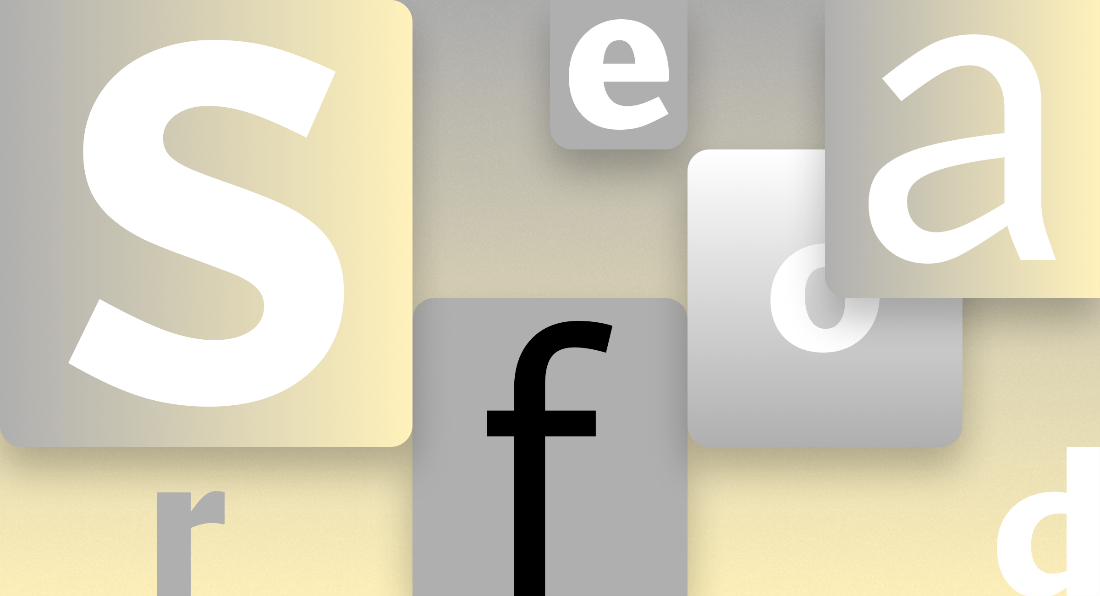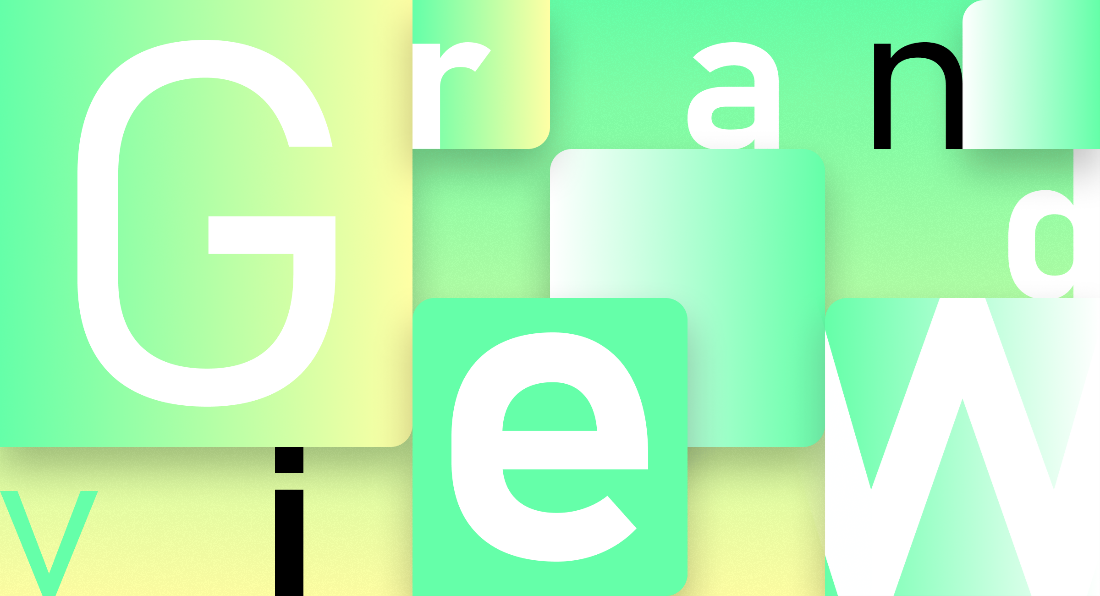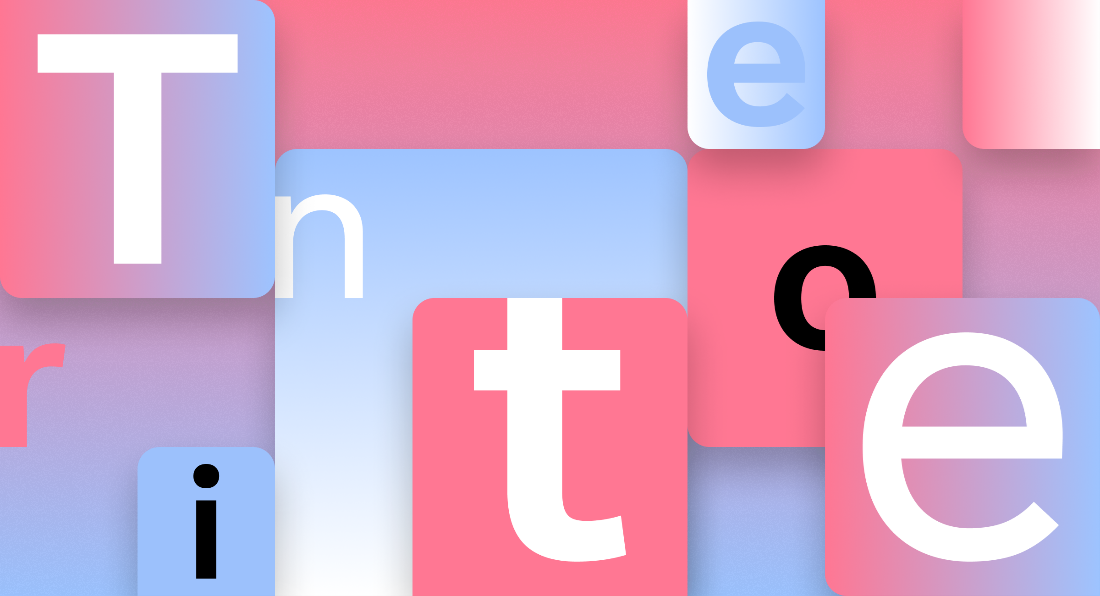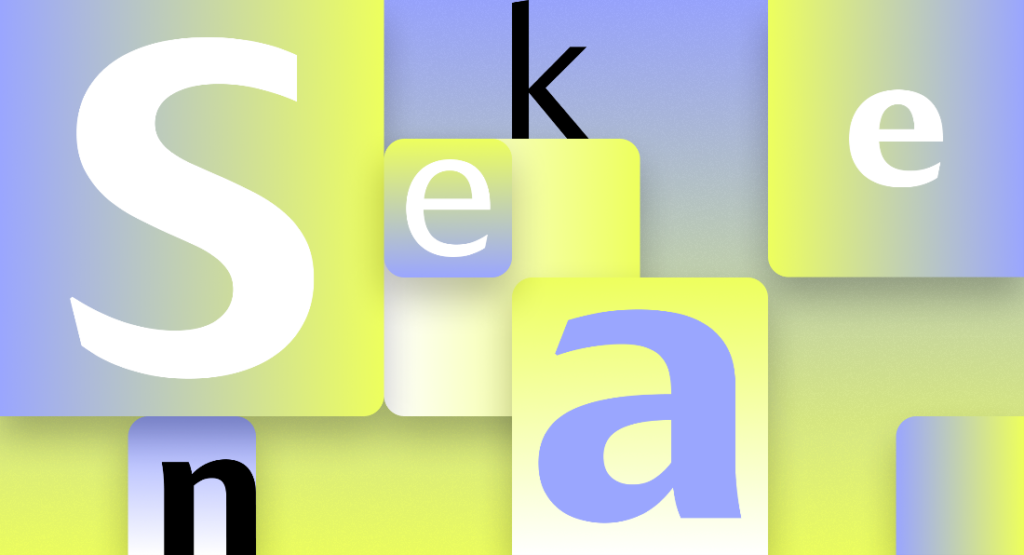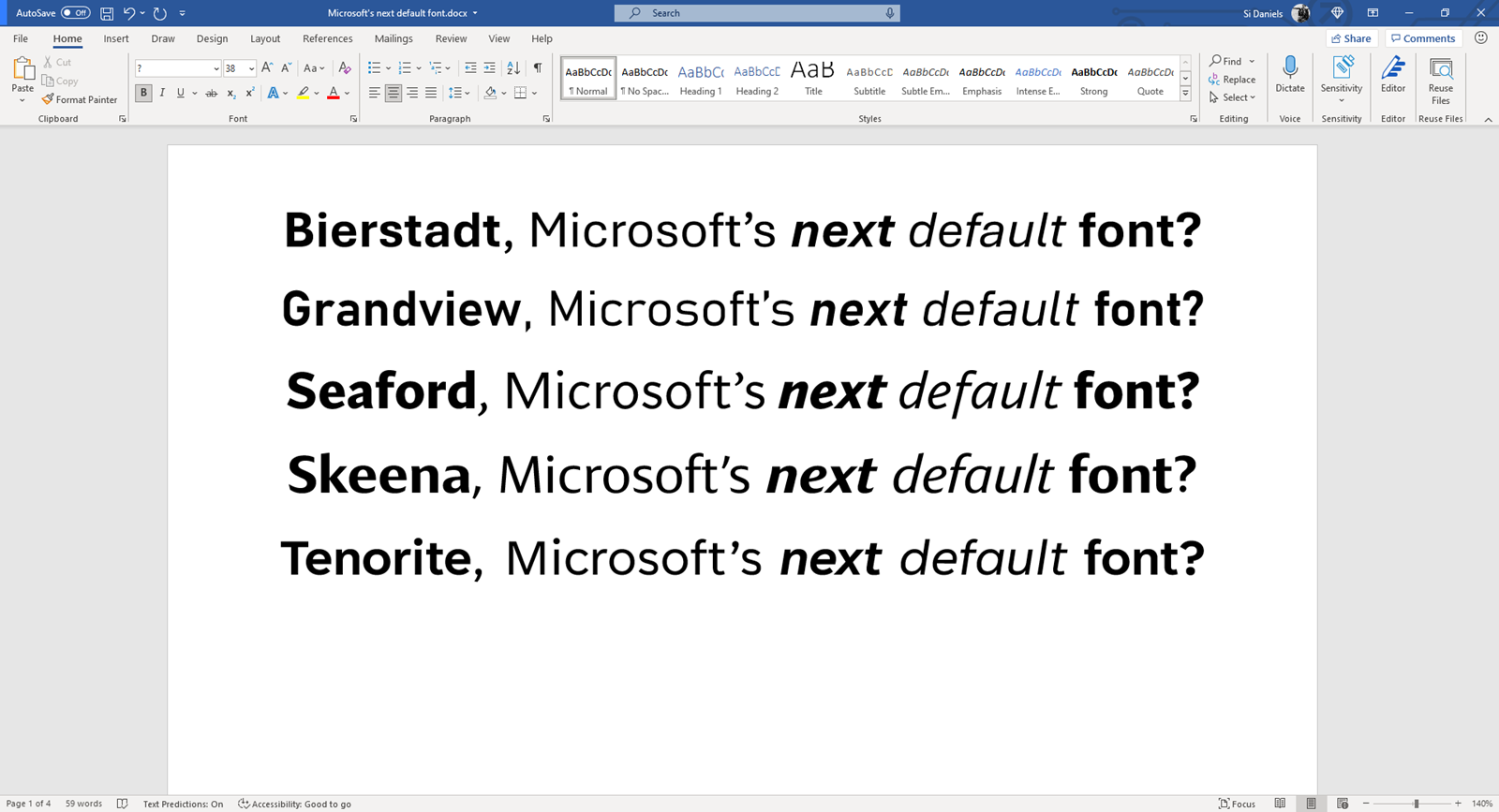
Microsoft mijenja zadani font Officea i traži povratne informacije korisnika
Calibri je korišten kao zadani font u Microsoft Officeu skoro 15 godina, pa Microsoft smatra da je promjena poželjna
Microsoft je objavio obavijest o zamjeni zadanog fonta unutar svoga programskog paketa Officea. Naime, promjena bi trebala stupiti na snagu već sljedeće godine, a tvrtka traži pomoć korisnika u vezi odabira novog zadanog fonta.
Korisnici će moći poslati povratne informacije u vezi pet novopredstavljenih sans serif fontova iz Microsoftove objave – Meet Tenorite, Bierstadt, Skeena, Seaford i Grandview. Navedeni fontovi sadrže, prema objavi tvrtke, razne stilove, uključujući humanistički, geometrijski, švicarski i industrijski.
Tenorite
Prvi od pet fontova, Tenorite, napravili su Erin McLaughlin i Wei Haung te izgleda najtradicionalnije. Iz Microsofta navode da Tenorite nalikuje Times New Romanu, ali da je više „topliji i srdačniji“. Font ima elemente kao što su velike točke, akcenti i interpunkcije koje ga čine ugodnijim za čitanje na zaslonu, a oštri mu oblici i široka slova daju na otvorenosti.
Bierstadt
Steve Mattison, inspiriran, švicarskom tipografijom iz sredine 20. stoljeća, napravio je drugi na listi font, Bierstadt. Naime, ovaj font nudi svestrani tip slova koja izražavaju jednostavnost i razumljivost u vrlo čitljivom obliku te je također vrlo jasno izražen završecima poteza koji ističu red, ali i suzdržanost. Bierstadt je nazvan po stjenovitoj planini u Koloradu koja je Mattisona podsjećala na švicarske Alpe.
Skeena
Treći je font Skeena, napravljen od strane Johna Hudsona i Paula Hanslowa, a inspiriran je raznim razdobljima dizajna fonta. Microsoft navodi da su potezi ovog fonta modularni s primjetnim kontrastom između debelih i tankih linija te da je idealan za tekst u dugim dokumentima, ali i kraćim odlomcima unutar prezentacija, brošura, tablica i izvješća.
Seaford
Tobias Frere-Jones, Nina Stössinger i Fred Shallcrass, napravili su klasični „old-school“ font Seaford. Naime, kako bi pronašli praktičan način da klasični font vrate u život bez serifa, dizajneri su inspiraciju vukli iz starih fotelja. U ovom se fontu ističe razlike između slova, pa se tako stvaraju prepoznatljivi oblici pojedinih riječi, što može biti vrlo ugodno za čitanje dužih tekstova.
Grandview
Posljednji font, Grandview, povlači inspiraciju iz klasičnih njemačkih cestovnih i željezničkih znakova. Dizajner koji stoji iza ovog fonta, Aaron Bell, napravio je font koji je, kako tvrde iz Microsofta, čitljiv na daljinu i pod lošim uvjetima, baš kao i prometni znakovi. Grandview je zamišljen za upotrebu u body tekstovima, no uz male se prilagodbe može koristiti i za duže čitanje.